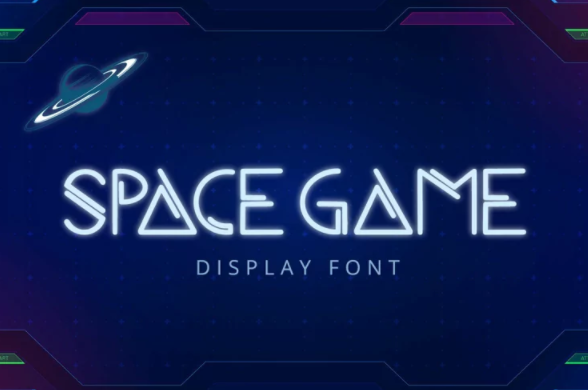
[Fontbundles] Space Game Font (2021)
Space Game - это шрифт с веселой и футуристической атмосферой. Он прекрасно подойдет для брендинга, дизайна логотипа, письма, логотипа, одежды, плаката, журнала, упаковки, постеров, сумок, футболок, обложек книг, фотографии, специальных мероприятий и других дизайнерских проектов.